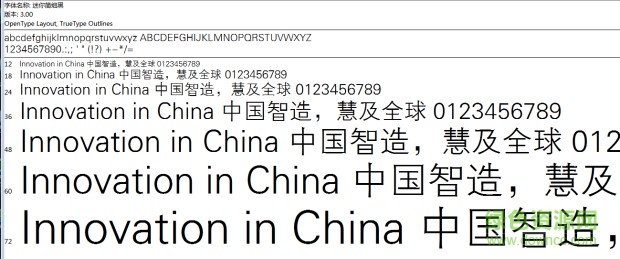
jxihei是什么字體?jxihei字體是一款迷你簡細黑字體,這款字體保留了黑體的一般特點,適用于書籍、畫報、海報宣傳、平面設計、卡通畫本等領域,非常的實用又便捷,也能突出重點,有需要者歡迎來綠色資源網(wǎng)免費下載!
大黑字體:具有渾厚凝重的氣 度,是印刷界中較為穩(wěn)重、醒目的標題字!
中黑字體:樸素大方、筆畫單純、結(jié)構(gòu)嚴謹,引人注目、實用性強。
粗黑字體:字型方正飽滿,筆劃粗重堅實,壯重醒目,號召力強!